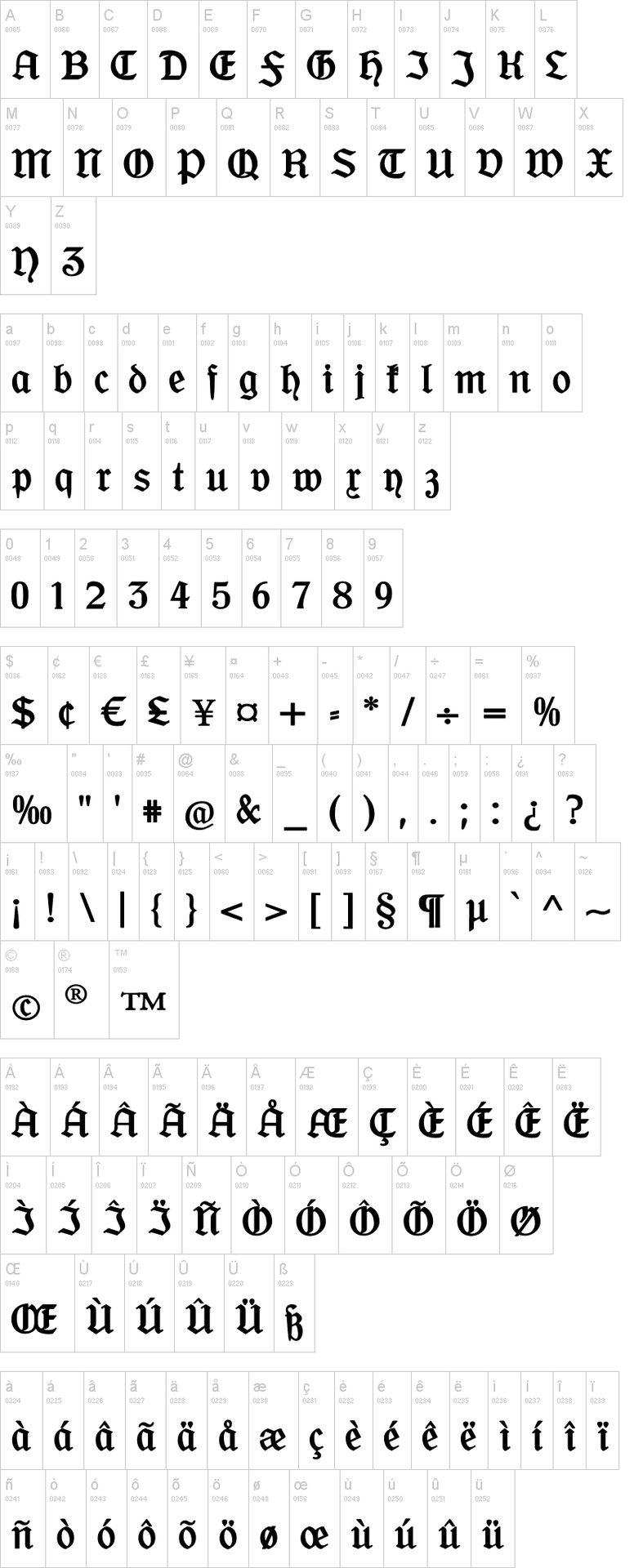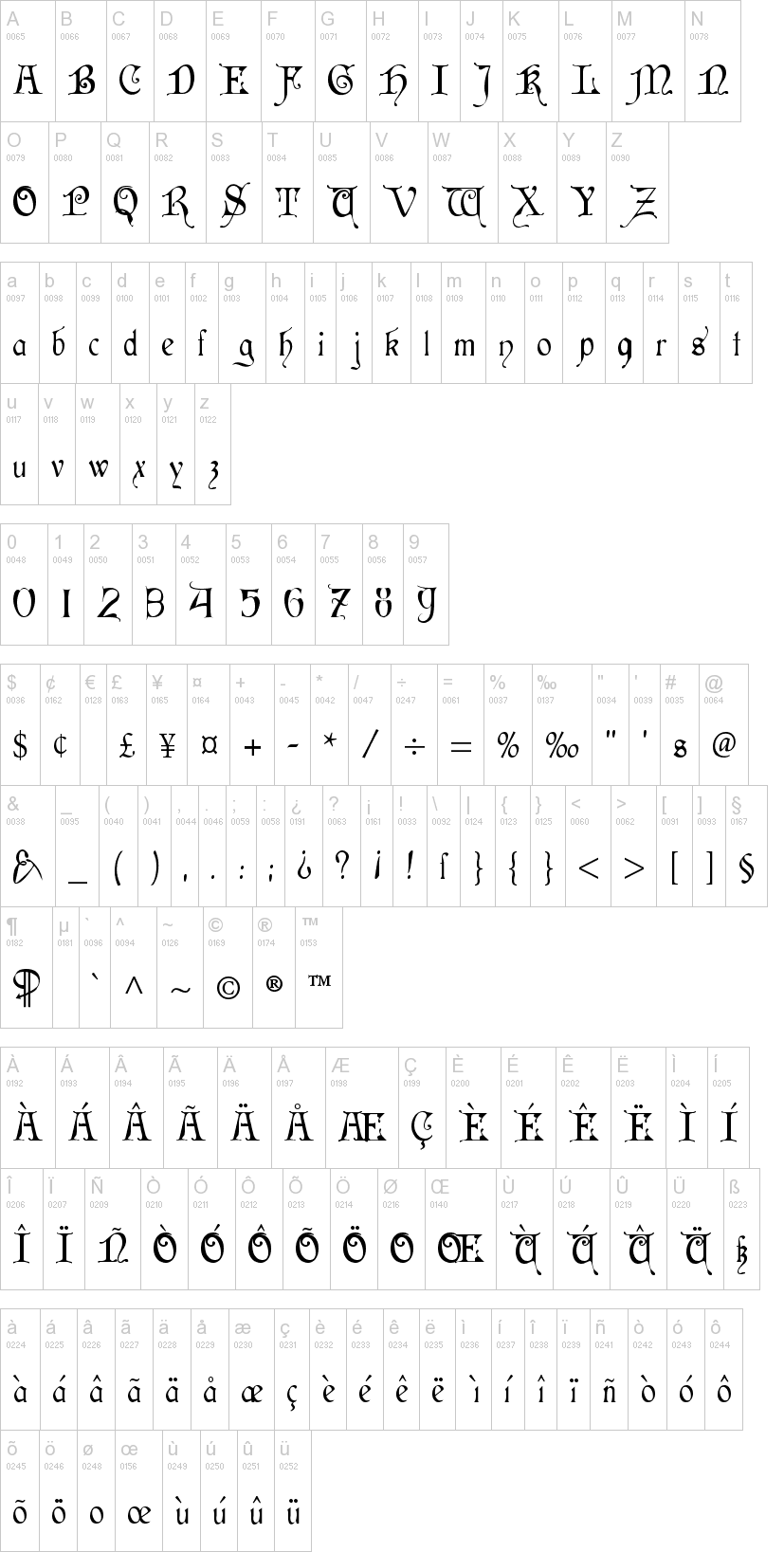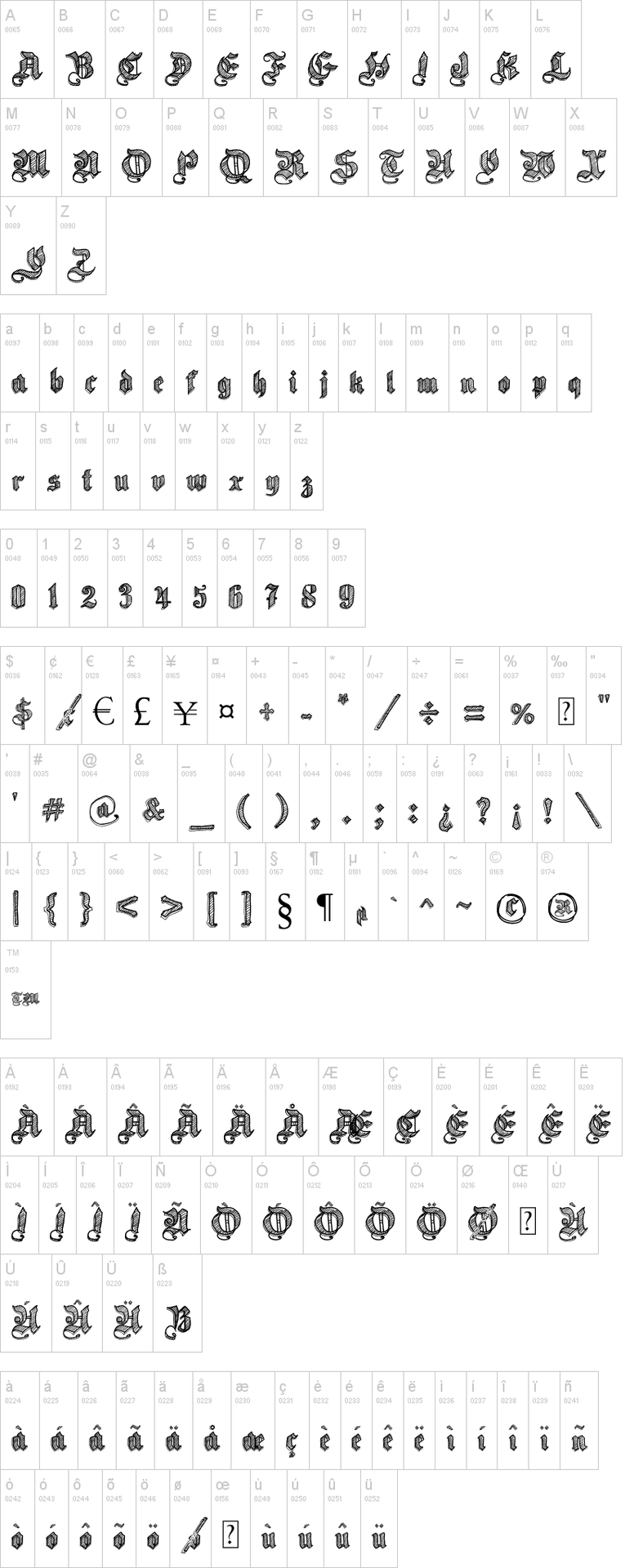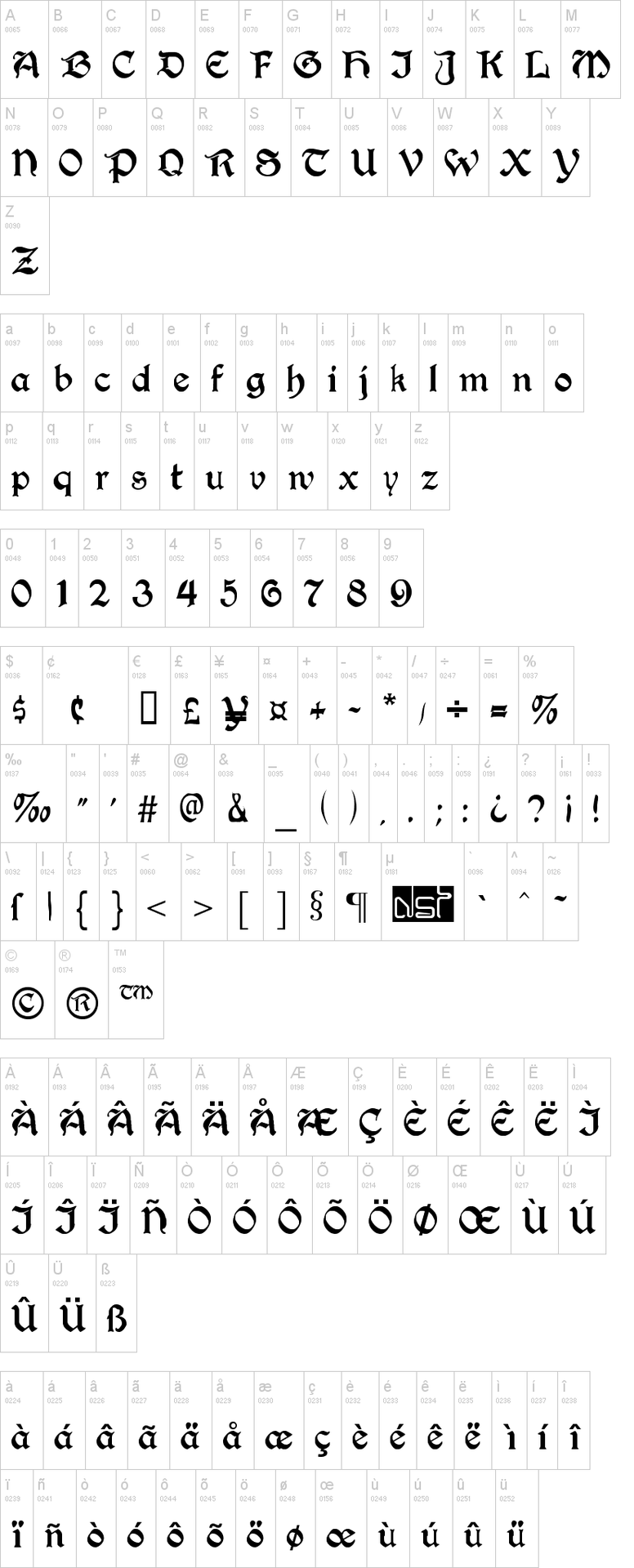
/GOTHIC FONTS/
* Những font này nên dùng khi edit graphic.
I, Old London
II,Cloister Black
III,Sketch Gothich School
IV, Cardinal Font :
V, Black Family
VI, Augusta
VII, Collins
VIII, DeiGratia
IX, Offenbacher Schwabacher CAT
X, BlackFlag Font